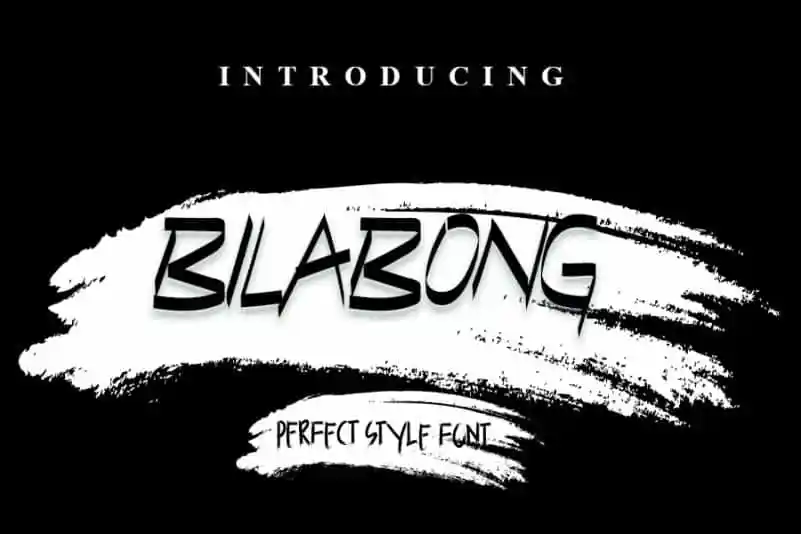
Bilabong Display Font – Download Grátis
A Bilabong Display Font é uma escolha perfeita para quem busca uma mistura atraente de influências chamigráficas clássicas e uma aparência contemporânea e fresca. Esta fonte atinge um excelente equilíbrio entre elegância vintage e modernidade, o que faz dela uma opção versátil para uma ampla variedade de ideias criativas. Seja para criações em papel como letras impressas ou selos, ou até mesmo para títulos impressionantes nas suas campanhas de marketing digital – a Bilabong Display será sua fonte perfeita. Esta fonte tem um charme único que faz dela uma ótima escolha para qualquer projeto onde você deseja destacar seu design e torná-lo ainda mais memorável.